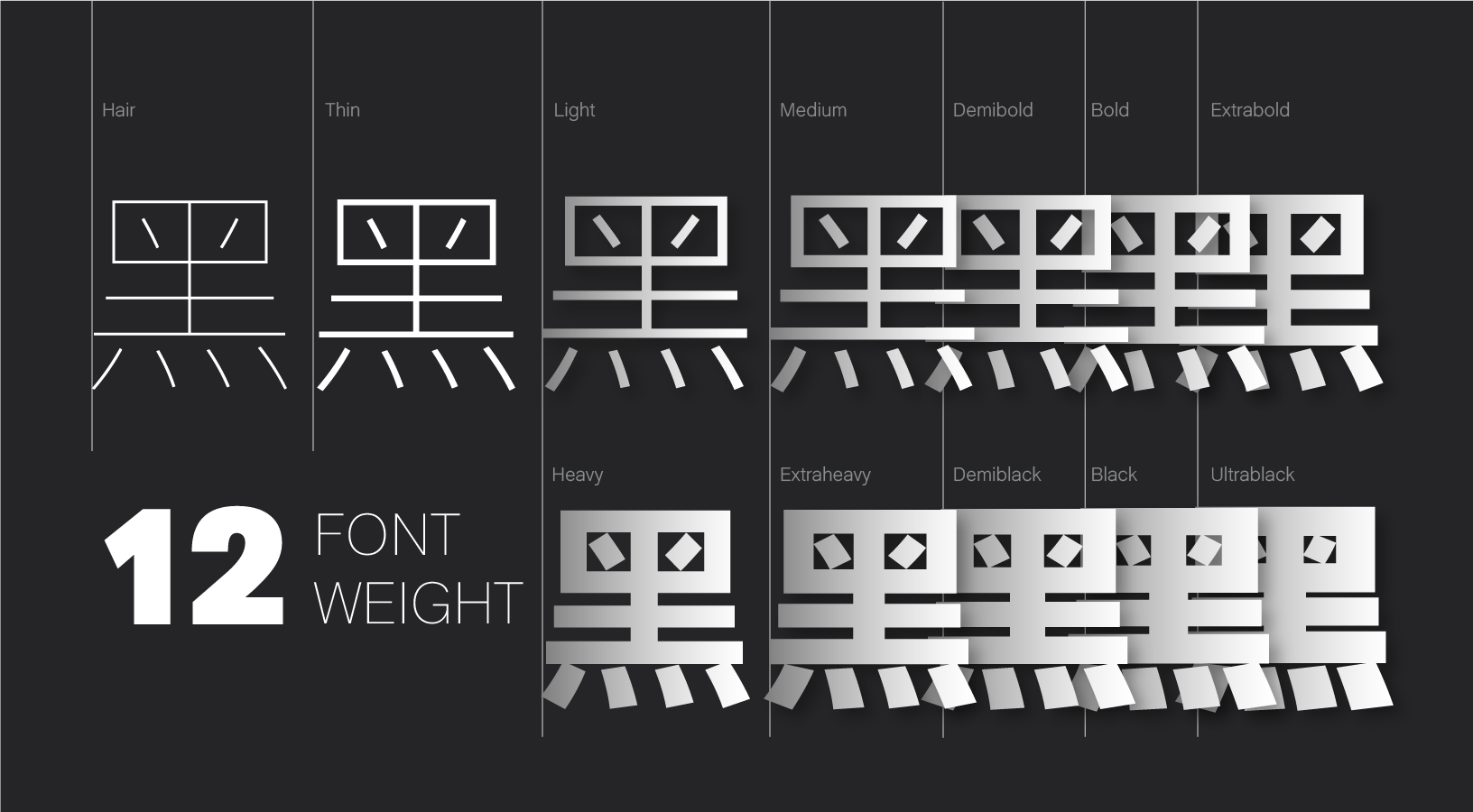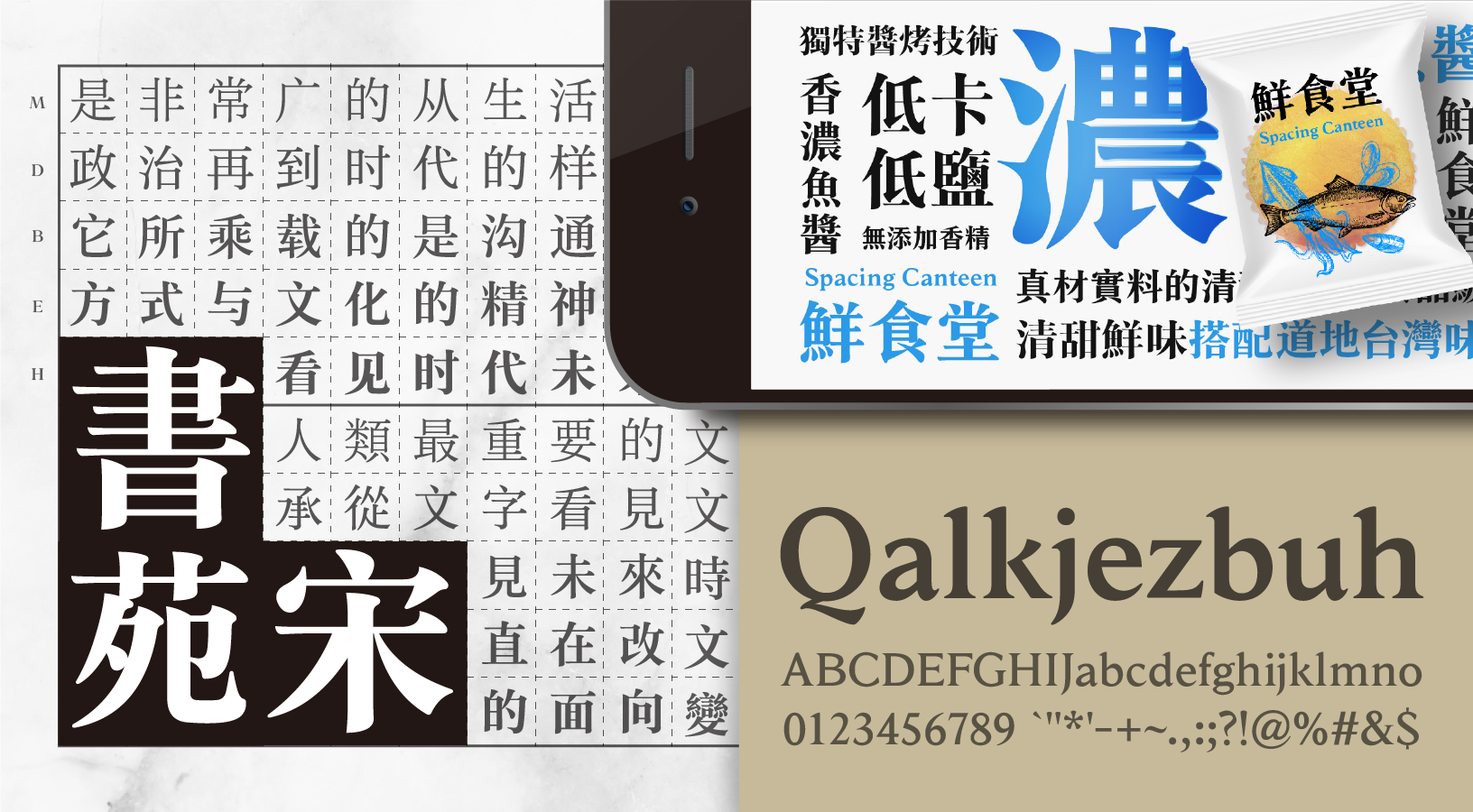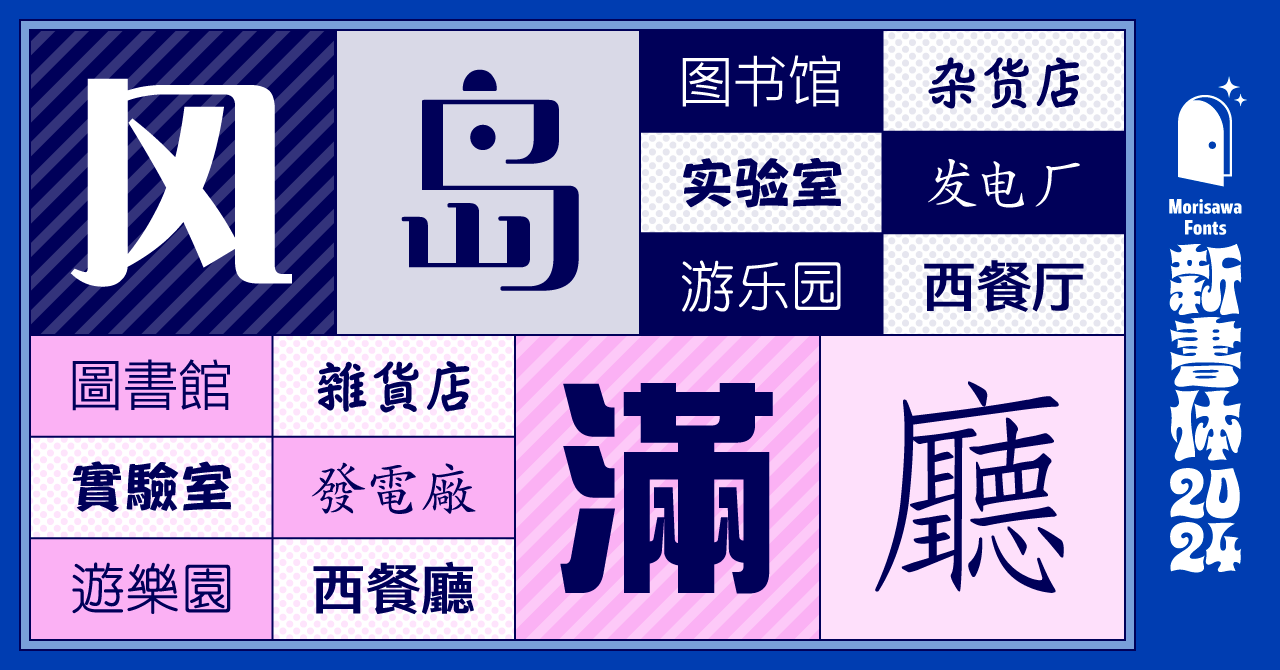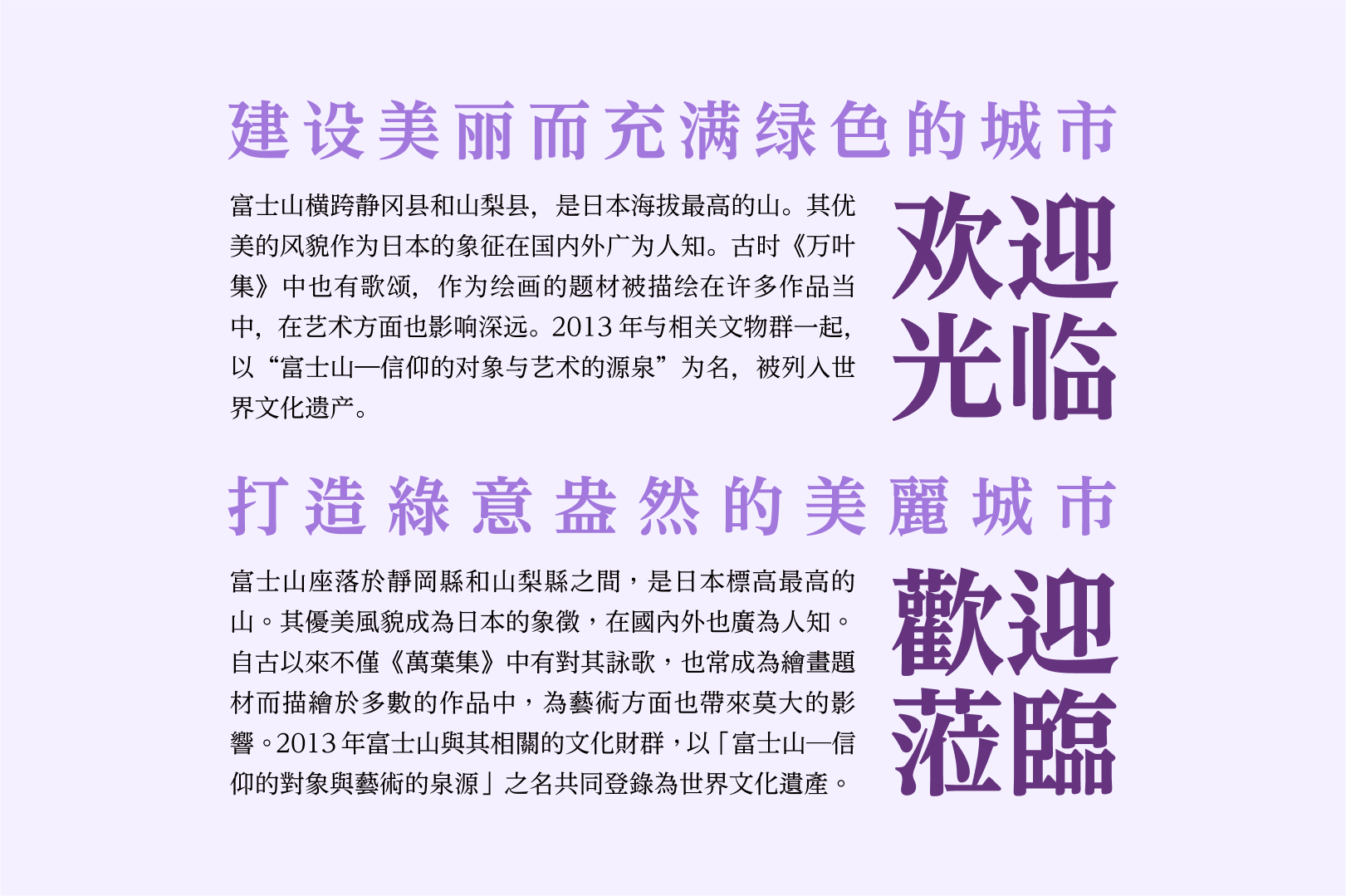
中国語フォントのバラエティ
簡体字と繁体字
適切な書体選びで、
効果的な情報発信を
簡体字と繁体字はいずれも中国語を表記するためのものです。簡体字は中華人民共和国、シンガポール、マレーシアで主に使われ、繁体字は台湾、香港、マカオなどで使用されている文字です。
Webサイトや掲示物、機器、ゲームなど、日本で中国語を使った表示を必要とする場合も、簡体字と繁体字を適切に使用することで、伝えたい相手に合わせた、正確な情報伝達が可能になります。
モリサワでは、定番書体の言語展開からArphic Typesのユニークなライブラリまで、バラエティ豊かな中国語フォントを多数揃え、CJKフォントのラインナップを充実させています。
※CJKフォントとは、中国語(Chinese)、日本語(Japanese)、韓国語(Korean)に対応したフォントの総称です。中国語簡体字(Simplified Chinese)、中国語繁体字(Traditional Chinese)を区別し、CCJKフォントとも表現されます。
日本語と調和するラインナップ
• UD新ゴ 簡体字・繁体字(標準字体)の組み画像
UD新ゴ 簡体字・繁体字(標準字体)
媒体やサイズを問わずわかりやすい、ユニバーサルデザインのゴシック体
和文書体「UD新ゴ」のデザインをベースに設計されたゴシック体です。「UD新ゴ」と同様に、ふところを広く設計することで視認性を高めています。「UD新ゴ」との併用を目的につくられた「Clarimo UD」シリーズや、「UD新ゴ ハングル」ともデザインが揃って見えるように設計されているため、日本語・簡体字・繁体字・英語・韓国語・タイ語・アラビア語・ヒンディー語などを併記する際にも統一したイメージの展開が可能です。また「UD新ゴ 繁体字」は、台湾の国字標準字体に則った字体を採用しています。
• UD黎ミン 簡体字・繁体字の組み画像
UD黎ミン 簡体字・繁体字
細い横画を使いやすい太さに設計した、ユニバーサルデザインの明朝体
和文書体「UD黎ミン」のデザインをベースに開発された明朝体の書体です。横画にしっかりと太みを持たせ、使いやすい太さに設計しています。「UD黎ミン ハングル」や「Lutes UD PE」と合わせて使用することで、日本語・簡体字・繁体字・韓国語・英語などを併記する際にも統一したイメージの展開が可能です。
• Arphic Typesのライブラリ×翠流シリーズの組み画像
Arphic Typesのライブラリ×翠流シリーズ
統一感のある多言語展開を、デザイン書体でも
翠流(すいりゅう)シリーズは、Arphic Typesの繁体字書体の漢字にモリサワで開発したかなをはじめとする非漢字を組み合わせた和文フォントです。Arphic Typesの簡体字・繁体字書体と翠流シリーズを合わせて使うことで、デザイン書体においても統一感のある多言語表記を実現します。
AR XinYi/翠流アトラス
AR QianZiBi/翠流くゆりペン
AR QiaoHei/翠流ゆゆポップ
AR Mochi H16C90/翠流きら星
AR RomanMing(簡体字のみ)/翠流ネオロマン・翠流デコロマン
Arphic Typesで広がる
中国語バリエーション
Arphic Types(アーフィック タイプス)は、1990年に台湾·台北で設立され、中国語フォント分野で長年の実績を持つフォントブランドです。繁体字フォントにおいて400書体以上、簡体字フォントが300書体以上、欧文フォントや日本語、韓国語、その他多言語フォントの開発実績もあります。
ベーシックな基本書体やグローバル展開のあるユニバーサルデザイン(UD)書体、トレンドを押さえたデザイン書体など幅広い書体ラインナップで中国語の表現をより豊かにします。
• AR UDJingXiHei(文鼎UD晶熙黑體)書体イメージ
AR UDJingXiHei(文鼎UD晶熙黑體)
• AR Mochi(文鼎白玉書體)書体イメージ
AR Mochi(文鼎白玉書體)
• AR ShuYuanSong(文鼎書苑宋)書体イメージ
AR ShuYuanSong(文鼎書苑宋)
• AR FangXinShu(文鼎方新書)書体イメージ
AR FangXinShu(文鼎方新書)
• AR XinYi(文鼎新藝體)書体イメージ
AR XinYi(文鼎新藝體)
• AR RomanMing(浪漫明朝体)書体イメージ
AR RomanMing(浪漫明朝体)
• AR HuaLi(文鼎花栗體)書体イメージ
AR HuaLi(文鼎花栗體)
• AR DCHYJianWei(文鼎DC黃陽尖魏體)書体イメージ
AR DCHYJianWei(文鼎DC黃陽尖魏體)
簡体字・繁体字の組見本
日本語と中国語の大きな違いは、句読点の位置や約物の使い方です。
簡体字の句読点の位置は日本式の「。」と同様で仮想ボディの左下になりますが、繁体字は伝統的には仮想ボディの中心に配置します。ただし、近年では日本と同じように右下に配置することもあります。 また句点には日本語と同じく「。」(マル)を使いますが、読点には「,」(カンマ)を使います。
中国に輸出する製品や中国で販売する製品に中国語フォント(簡体字)を搭載する場合は、中国の国家標準規格であるGB規格に準拠したフォントを使用する必要があります。